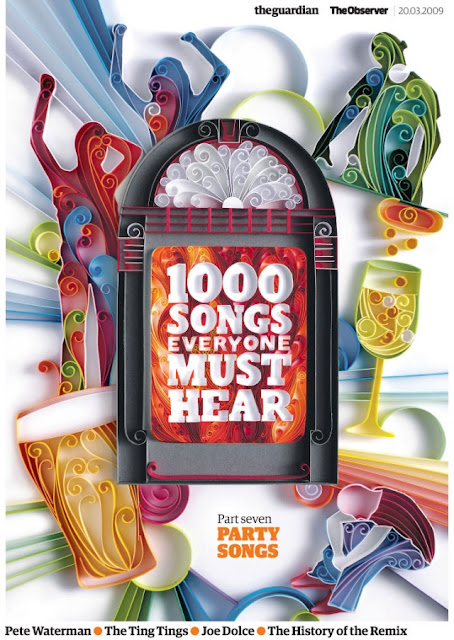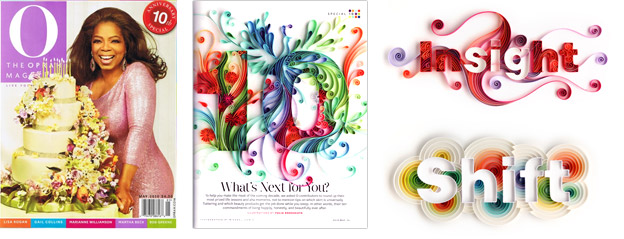
¡¡ Hola amigos de Lettering Time!! Una vez pasada las navidades y ya centrados de pleno en el 2018 os traemos material nuevo de calidad. Hoy volvemos con la serie de entrevistas que estamos llevando a cabo desde Lettering Time con los mayores y mas populares referentes de la caligrafia, el lettering, tipografĂa, sign painting, etc. En esta nueva serie de entrevistas ya han pasado por aquĂ el gran maestro peruano de las letras en gran formato, Elliot Tupac, los genios de la caligrafĂa, Luca Barcellona y Jackson Alves, ahĂ es nada:
Hoy os traemos algo que seguro os va a gustar, esta con todo nosotros la reina de las letras handmade, Yulia Brodskaya.
A lo largo de estos Ăşltimos años se ha producido una combinaciĂłn explosiva, el fuerte interĂ©s por la letra más el enorme auge de la cultura “handmade”, ha hecho que hayamos visto letras realizadas con casi cualquier tipo de material real, desde madera, pasando por cafĂ©, azĂşcar o cualquier otro tipo de alimento, hasta los materiales mas inimaginables. Pero sin duda alguna, la mayor referente de esta corriente es Yulia Brodskaya con sus fabulosos y profesionales proyectos con tiras de papel.
Yulia, rusa pero afincada en Londres, es una diseñadora especializada en proyectos realizados a mano mediante la tĂ©cnica llama “Quilling”, con los que ha asombrado al mundo y ha llamado la atenciĂłn de clientes de cualquier parte del globo.
Si no me equivoco, estas formas tridimensionales que realizas con tiras de papel es conocidos como "Quilling" ¿CĂłmo nace tu interĂ©s por este estilo y que es lo que te llamĂł la atenciĂłn de este mĂ©todo en particular?
Mi formaciĂłn es en diseño gráfico, pero siempre he tenido la tendencia a realizar trabajos hechos a mano, especialmente con papel. Me llevo un tiempo encontrar mi propia manera de combinar mi amor por el papel con mi experiencia y conocimiento en el diseño gráfico, la tipografĂa e ilustraciĂłn. EmpecĂ© a usar la tĂ©cnica del papel a laminas hace más de 6 años, pero yo no siempre lo he llamado “Quilling”, porque realmente he descubierto una nueva forma de usar esta tĂ©cnica básica, consiguiendo trabajarlo como si estuviera dibujando con papel y el “Quilling” tradicional está limitado por el uso de formas básicas.
La primera de estas obras de papel que hice fue mi nombre ‘Yulia’. Yo querĂa hacer un folleto pequeño para promocionar mis ilustraciones dibujadas a mano y estaba buscando una manera llamativa para ilustrar mi nombre en la portada. De alguna manera, me acordĂ© de este mĂ©todo de tiras de papel (en ese momento no tenĂa ni idea que se llamaba “Quilling”) y simplemente decidĂ usar este mĂ©todo para hacer las letras. Ese fue el punto de partida para mis experimentos, y aun hoy sigo experimentando, por que esta tĂ©cnica es muy versátil, y eso hace que mi estilo este en constante evoluciĂłn, y es precisamente esto lo que me gusta.
Por favor, cuéntanos tu proceso de trabajo.
Siempre empiezo haciendo bocetos a lápiz y no empiezo el 'papeleo' hasta que los bocetos son aprobados por los clientes (o estoy totalmente satisfecha con el resultado, si se trata de un trabajo personal). El bocetado es una etapa muy importante, porque una vez que pegue el primer trozo de papel ya no puedo echar marcha atrás (el pegamento se supone que es un adhesivo fuerte), por lo tanto, no hay lugar para errores y tengo que tener una idea muy clara de lo que estoy haciendo desde el principio.
Sin embargo, siempre hay espacio para los experimentos con el papel real, porque a veces es difĂcil ver lo que va a quedar bien antes de iniciar el trabajo con el papel. Una vez que la obra está lista, se fotografĂa.
La paciencia es, sin duda, una de las facultades que debes dominar para trabajar con esta tĂ©cnica, ¿Como llevas esto? ¿Cuantas horas le puedes dedicar a un diseño? ¿Cual es el trabajo que te ha llevado mas tiempo de realizar?
Yo no cuento las horas, al contrario, yo trato de distraerme un poco durante el proceso de trabajo escuchando audiolibros o 'viendo' programas de cocina con el rabillo del ojo, etc. Una de las obras más larga, me llevĂł alrededor de un mes realizarla, pero esta es una estimaciĂłn muy aproximada, porque yo mientras tanto estaba realizando trabajos comerciales. Puedo hacer un trabajo rápido en 2-3 dĂas si es necesario.
¿CĂłmo de importante es la letra en tu trabajo? Supongo que realizar letras con esta tĂ©cnica no es algo sencillo ¿QuĂ© dificultades te encuentras en este sentido?
Siempre me gustĂł la tipografĂa, supongo que esto es debido a mis antecedentes en diseño gráfico; citando a otras personas, “hago Quilling más fresco, moderno y di a esta antigua tĂ©cnica artesanal una nueva vida”. Yo creo que todo esto es debido a que empecĂ© a incorporar la tipografĂa a la práctica tradicional de este arte con papel.
Mantener la legibilidad es esencial para transmitir el mensaje que se desea, ¿Como es el proceso que realizas para las letras y palabras con el arte que tu realizas?
La legibilidad es algo que siempre está en desacuerdo con esta tĂ©cnica. SĂłlo trato de asegurarme de que no hago titulares muy largos y de no usar tipos de letra demasiado delgados o demasiado gruesos. Para ciertos proyecto, tengo que incorporar tipografĂa digital con el fin de mantener el texto legible, ya que a veces es bueno tener texto digital nĂtido al lado del hecho a mano, porque todas las letras hechas a mano, en ocasiones, resulta demasiado abrumador.
Hasta aquĂ la entrevista de hoy. Espero os haya resultado interesante conocer mas acerca del trabajo de esta gran profesional, Yulia Brodskay, y del mundo del Quilling ;)